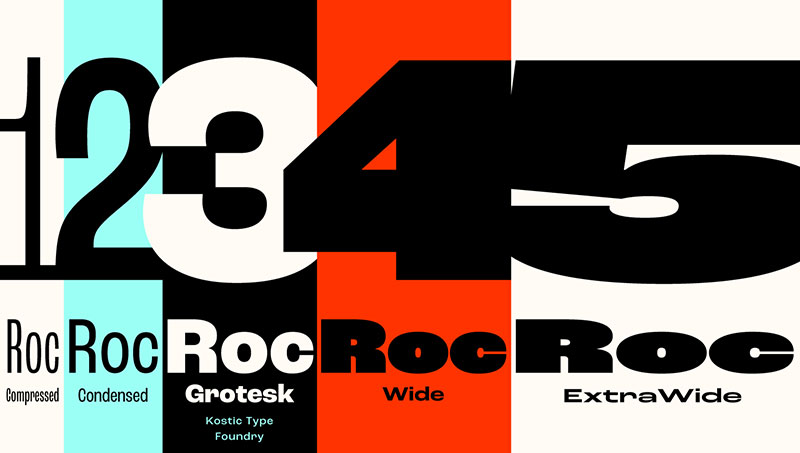
Stellen Sie sich vor, Sie tauchen in eine Welt ein, in der jeder Buchstabe eine Geschichte erzählt. Das ist die Kraft der besten Schriften für Grafikdesign.
Schriften sind mehr als nur Buchstaben auf einer Seite; sie sind die Stimme Ihrer Marke, der Ton Ihrer Nachricht und die Persönlichkeit Ihres Designs.
Auf dieser Reise werden wir das Geheimnis hinter der Auswahl der perfekten Schrift lüften. Egal, ob Sie ein schlankes Logo entwerfen oder eine herausragende Webseite gestalten, die richtige Schrift kann Ihr Design machen oder brechen.
Ich werde Sie durch das Labyrinth von Serifen und serifenlosen Schriften führen, Sie mit dem Charme von Schreibschriften bekannt machen und Ihnen zeigen, wie Sie die Wirkung von Display-Schriften nutzen können.
Sie werden nicht nur über Ästhetik lernen, sondern auch über die Feinheiten der Schriftlesbarkeit und typografischen Trends.
Von der Kühnheit der Helvetica bis zur Eleganz der Garamond hat jede Schrift ihre eigene Geschichte. Am Ende werden Sie in der Lage sein, Schriftauswahlen zu treffen, die nicht nur gut aussehen, sondern auch viel aussagen.
Die besten Schriften für Grafikdesign
| Schrift | Kategorie | Serif/Serifenlos | Verwendung | Bemerkenswerte Merkmale |
|---|---|---|---|---|
| Garamond | Altmodisch | Mit Serifen | Fließtext, Druck | Elegant, lesbar, Stil der französischen Renaissance |
| Baskerville | Übergangszeit | Mit Serifen | Druck, Luxus | Scharf, hoher Kontrast, Gefühl der englischen Aufklärung |
| Times New Roman | Übergangszeit | Mit Serifen | Zeitungen, Fließtext | Allgegenwärtig, kompakt, praktisch |
| Bodoni | Modern | Mit Serifen | Schlagzeilen, Poster | Extremer Kontrast zwischen dicken und dünnen Linien |
| Georgia | Modern | Mit Serifen | Digitale Bildschirme | Sehr lesbar auf Bildschirmen, robust |
| Financier Display | Neo-grotesk | Mit Serifen | Finanzberichte | Anspruchsvoll, zeitgenössisch, optimiert für Display-Nutzung |
| Helvetica | Neo-grotesk | Ohne Serifen | Allgemein, Beschilderung | Neutral, klar, sehr beliebt |
| Arial | Grotesk | Ohne Serifen | Allgemeine digitale Nutzung | Häufig, Alternative zu Helvetica |
| Univers | Grotesk | Ohne Serifen | Verschiedenes | Breites Spektrum an Varianten, klar, funktional |
| Futura | Geometrisch | Ohne Serifen | Branding, Poster | Geometrische Formen, modern |
| Avenir | Geometrisch | Ohne Serifen | Unternehmensdesign | Modern, humanistische Akzente, klar |
| Neue Haas Grotesk | Neo-grotesk | Ohne Serifen | Typografie, Branding | Ursprünglicher Name von Helvetica, originalgetreu |
| Blimey | Display | Ohne Serifen | Schlagzeilen, dekorativ | Ausdrucksstark, kreativ |
| Cheee | Display | Ohne Serifen | Leger, komödiantisch | Eigenartig, spaßig, informell |
| BD Supper | Display | Ohne Serifen | Poster, Branding | Fett, wirkungsvoll |
| Beverly Drive | Schreibschrift | Ohne Serifen | Branding, Mode | Elegante Kursivschrift |
| Swear Display | Mit Serifen | Redaktion, Luxus | Raffiniert, hoher Kontrast |
| Trade Gothic | Gotisch | Ohne Serifen | Werbung, Text | Direkt, unkompliziert |
| Roc Grotesk | Ohne Serifen | Allgemeine Nutzung | Vielseitig, zeitgenössisch, breites Gewichtsspektrum |
| Atyp | Display | Ohne Serifen | Poster, künstlerisch | Einzigartig, originell |
| Byker | Display | Ohne Serifen | Urban, jugendlich | Kantig, zeitgenössisch |
| Forrest | Handschrift | Ohne Serifen | Legerer Text, informell | Freundlich, organisch |
| MD Nichrome | Grotesk | Ohne Serifen | Web, Redaktion | Modern, minimalistisches Gefühl |
| Dunbar | Ohne Serifen | Display | Schlagzeilen, Luxus | Große x-Höhe, stilisiert |
| Gooper | Display | Ohne Serifen | Poster, auffällig | Klobig, übertrieben |
| Bilo | Display/Dekorativ | Ohne Serifen | Spaßthemen, verspielt | Handgezeichnet, informell |
Beliebte Serifenschriften
Serifenschriften, diese klassischen Schönheiten mit kleinen Füßen am Ende jedes Buchstabens, sind ein Eckpfeiler in der Welt der besten Schriften für Grafikdesign.
Sie bringen einen Hauch von Eleganz, Tradition und ein gewisses ‚je ne sais quoi‘ auf den Tisch. Tauchen wir ein und erkunden einige der bekanntesten und zeitlosesten Serifenschriften sowie einige moderne Interpretationen dieses klassischen Stils.
Zeitlose Klassiker
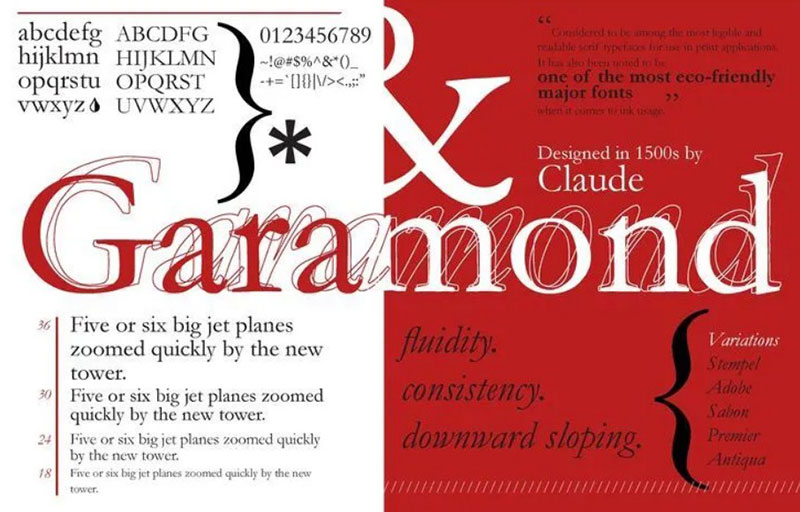
Garamond, ah, die alte Seele der Typografie. Es ist wie dieser Vintage-Wein – wird mit der Zeit immer besser.
Perfekt für diejenigen, die einen Hauch von Geschichte in ihren Designs lieben. Garamond ist nicht nur eine Schrift; es ist ein Geschichtenerzähler, der seit dem 16. Jahrhundert existiert und damit eine erste Wahl für Buchgestalter und Verleger ist.
Mit seiner klassischen Eleganz und Lesbarkeit nimmt Garamond einen besonderen Platz im Herzen der Typografie ein.
Weiter geht’s mit Baskerville. Diese Schrift balanciert die feine Linie zwischen Respektabilität und Flair.
Im 18. Jahrhundert entworfen, hat Baskerville diese einzigartige Fähigkeit, jeden Text sofort anspruchsvoller aussehen zu lassen. Es ist wie der maßgeschneiderte Anzug der Schriftwelt – sieht immer gut aus, egal zu welchem Anlass.
Und dann gibt es das allgegenwärtige Times New Roman. Lieben oder hassen Sie es, man kann seine Omnipräsenz nicht leugnen.
Es ist wie das Brot und Butter der Schriften – zuverlässig, vertraut und erledigt die Arbeit. Obwohl es manche als ‚Standard‘ bezeichnen mögen, ist Times New Roman in der Welt der besten Schriften für Grafikdesign ein Klassiker, der bleiben wird.
Moderne Serifenschriften
Jetzt wird es aufregend mit einigen modernen Serifenschriften. Bodonimit seinem dramatischen Kontrast zwischen dicken und dünnen Strichen schreit nach Luxus.
Es ist wie das High-Fashion-Model der Schriften – glamourös und auffällig. Perfekt für Schlagzeilen, Logos und jedes Projekt, bei dem Sie eine Aussage machen möchten.
Als Nächstes, Georgia. Speziell für die Lesbarkeit auf Bildschirmen entwickelt, ist es der freundliche Nachbar unter den Serifenschriften.
Anspruchslos, vielseitig und selbst in kleinen Größen gut lesbar, ist Georgia eine solide Wahl für Webinhalte und digitales Design.
Zu guter Letzt, Financier Display. Diese Schrift bringt einen zeitgenössischen Twist zum traditionellen Serifen.
Es ist wie jener coole, raffinierte Freund, der weiß, wie man die Dinge interessant hält. Mit seiner starken Persönlichkeit und hohen Lesbarkeit ist Financier Display großartig für moderne Marken, die sich abheben wollen.
Einflussreiche serifenlose Schriften
Serifenlose Schriften sind wie der coole, minimalistische Cousin in der Familie der besten Schriften für Grafikdesign.
Sie sind sauber, klar und oh-so-modern. Serifenlose Schriften verzichten auf die kleinen Füße (Serifen) für einen gestraffteren, geradlinigeren Look.
Perfekt für alles, von kräftigen Schlagzeilen bis hin zu leicht lesbarem Fließtext, sind diese Schriften eine erste Wahl für Grafikdesigner, die eine schlanke Aussage machen möchten.
Klassische serifenlose Schriften
Zuerst sprechen wir über Helvetica. Sie ist wie das Schweizer Taschenmesser der Schriften – vielseitig, funktional und super beliebt.
Helvetica ist überall, von U-Bahn-Schildern bis zu Logos von Technologieunternehmen. Sie ist der Inbegriff der Philosophie ‚weniger ist mehr‘ im Design.
Schlicht und doch kraftvoll ist Helvetica ein Muss in jedem Designer-Toolkit.
Dann gibt es Arial. Denken Sie daran als jüngeren Geschwister von Helvetica. Es ist super häufig (Sie haben es wahrscheinlich auf Ihrem Computer gesehen) und unglaublich benutzerfreundlich.
Arial ist wie der freundliche Nachbar, der immer da ist, wenn Sie ihn brauchen. Es ist großartig für digitale Projekte, besonders wenn Lesbarkeit wichtig ist.
Und wir dürfen nicht Univers vergessen. Diese Schrift dreht sich alles um Konsistenz und Klarheit. Es ist wie der methodische, organisierte Freund, der Sie nie im Stich lässt.
Mit einer Reihe von Gewichten und Stilen bietet Univers Flexibilität und behält dabei sein sauberes, ungehindertes Erscheinungsbild bei. Es ist eine Top-Wahl für Unternehmens- und Redaktionsdesign.
Zeitgenössische serifenlose Schriften
Jetzt zu den neueren Stars der serifenlosen Welt. Futura ist wie der fortschrittliche, trendsetzende Schrifttyp.
Mit seinen geometrischen Formen und gleichmäßiger Gewichtsverteilung hat es eine futuristische Atmosphäre, die perfekt für innovative Marken und moderne Kunstprojekte ist.
Als nächstes, Avenir. Diese Schrift ist wie der coole, jüngere Cousin von Futura. Es geht mehr um Balance und Harmonie, weniger um scharfe Kanten.
Avenir bringt eine Note Wärme in die oft kalte und unpersönliche Welt der serifenlosen Schriften. Es ist großartig für Benutzeroberflächen, digitale Inhalte und überall dort, wo Sie einen Hauch von moderner Eleganz wünschen.
Zuletzt, aber definitiv nicht zuletzt, Neue Haas Grotesk. Denken Sie daran als die ursprüngliche, ungefilterte Version von Helvetica.
Es hat etwas mehr Charakter, etwas mehr Eigenart. Neue Haas Grotesk ist für diejenigen, die Helvetica lieben, aber etwas mit etwas mehr Persönlichkeit möchten.
Einzigartige Display- und Schreibschriften
Wenn wir über die besten Schriften für Grafikdesign sprechen, ist es wie eine Schatzkiste zu öffnen, wenn wir über einzigartige Display- und Schreibschriften sprechen.
Diese sind nicht Ihre alltäglichen Schriftarten; sie sind die Showstopper, diejenigen, die Ihr Design schreien lassen ‚Schau mich an!‘.
Sie sind perfekt, wenn Sie Persönlichkeit, Flair und ein wenig Drama in Ihre Arbeiten einbringen müssen. Lassen Sie uns einige dieser bahnbrechenden Schriften durchgehen.
Display-Schriften für Impact
Schon mal von Blimey gehört? Es ist wie das Leben der Party in der Schriftwelt. Fett, laut und unverschämt spaßig, Blimey ist perfekt, um Aufmerksamkeit zu erregen. Verwenden Sie es für Schlagzeilen, Poster oder jedes Projekt, bei dem Sie möchten, dass die Worte vom Bildschirm oder von der Seite springen.
Cheee ist ein weiteres Juwel. Stellen Sie sich den schrulligen Freund vor, der immer in einer Menschenmenge auffällt. Cheee ist einzigartig, verspielt und perfekt für Projekte, die ein wenig Verspieltheit benötigen. Es ist großartig für kreative Branding, funky Anzeigen oder sogar, um ein wenig Funken in Social-Media-Grafiken zu bringen.
Dann gibt es BD Supper. Stellen Sie sich eine Schrift vor, die sowohl stark als auch elegant ist, wie ein gut geschnittener Anzug. Es ist anspruchsvoll, aber nicht steif, was es ideal für High-End-Branding, Magazin-Header oder jedes Design macht, das einen Hauch von Klasse benötigt.
Elegante Schreibschriften
Wenn wir zur eleganten Seite der Dinge wechseln, sind Schreibschriften wie Beverly Drive die handgeschriebenen Liebesbriefe der Schriftwelt.
Beverly Drive mit seinen sanften, fließenden Linien fügt jedem Projekt eine persönliche, handgemachte Note hinzu. Es ist perfekt für Hochzeitseinladungen, Boutique-Branding oder alles, was einen Hauch von Eleganz benötigt.
Swear Display ist eine weitere Schönheit. Denken Sie daran als den künstlerischen, freigeistigen Typ. Es ist perfekt, wenn Sie ein wenig Flair und Raffinesse hinzufügen möchten. Ideal für Buchcover, Branding oder jedes Projekt, bei dem Sie möchten, dass die Schrift nicht nur gesehen, sondern gefühlt wird.
Vielseitige und funktionale Schriften
Wenn wir über die besten Schriften für Grafikdesign sprechen, sind Vielseitigkeit und Funktionalität der Schlüssel.
Dies sind die Schriften, die alles können – von laut schreiend auf einem Poster bis hin zu sanft flüsternd in einem Bericht. Sie sind wie das Multitool in Ihrem Design-Kit. Lassen Sie uns einige Schriften durchgehen, die ziemlich alles bewältigen können, was Sie ihnen anvertrauen.
Arbeitsschriften für verschiedene Anwendungen
Trade Gothic ist wie dieser zuverlässige Freund, der immer für Sie da ist. Es ist unkompliziert, nüchtern und erledigt die Arbeit.
Diese Schrift ist perfekt für die Zeiten, in denen Sie möchten, dass Ihre Nachricht klar und ungehindert ist. Es ist großartig für alles, von Fließtext in einem Bericht bis hin zu einer starken Schlagzeile in einer Anzeige.
Als nächstes, Roc Grotesk. Denken Sie daran als das Chamäleon der Schriftwelt. Es passt nahtlos in jedes Design, an dem Sie arbeiten Entschuldigen Sie bitte die Unterbrechung. Lassen Sie uns den Abschnitt fortsetzen.
Roc Grotesk ist wie das Chamäleon der Schriftwelt. Es passt nahtlos in jedes Design, an dem Sie arbeiten. Mit seiner breiten Palette an Gewichten kann Roc Grotesk laut oder leise, oder alles dazwischen sein. Es ist super vielseitig, was es zu einer Top-Wahl für Branding, Webdesign und redaktionelle Arbeit macht.
Und dann gibt es Atyp. Diese Schrift ist wie der coole, kantige Typ in der Gruppe. Sie ist modern, dynamisch und sticht hervor. Verwenden Sie Atyp, wenn Sie Ihrem Design eine zeitgenössische Wendung geben möchten. Es ist großartig für kreative Projekte, digitalen Inhalt und überall dort, wo Sie eine Aussage machen möchten.
Schriften für Spezialanwendungen
Manchmal benötigen Sie eine Schrift, die für einen bestimmten Zweck gemacht ist. Byker ist wie der Technikwizard in der Schriftwelt. Entworfen für technische Projekte, hat es ein mechanisches Gefühl, das perfekt für alles von Bedienungsanleitungen bis zu technischen Zeichnungen ist.
Forrest ist eine weitere spezielle Schrift. Stellen Sie sich eine warme, ansprechbare Schriftart mit einer Prise Eigenartigkeit vor. Forrest ist eine abgerundete Serifenschrift, die sich von der Masse abhebt. Sie ist perfekt für Kinderbücher, spielerisches Branding oder jedes Projekt, das eine freundliche Note benötigt.
Aktuelle Trends in der Typografie
In der sich ständig weiterentwickelnden Welt der besten Schriften für Grafikdesign ist es aufregend, die neuesten Trends zu verfolgen – es ist spannend und absolut lohnenswert.
Typografietrends sind der Herzschlag der Designinnovation und formen ständig neu, wie wir visuell ausdrücken und kommunizieren. Tauchen wir ein, was gerade Wellen schlägt.
Retro- und nostalgische Einflüsse
Zuerst sprechen wir über die Comeback-Kinder – Retro- und nostalgische Einflüsse. Schriften wie MD Nichrome bringen die Vibes vergangener Jahre mit einem modernen Dreh zurück.
Es ist, als hätte man einen Fuß in der Vergangenheit, während die Augen auf die Zukunft gerichtet sind. Diese Schriften vermischen alten Charme mit zeitgenössischem Flair und sind perfekt für Marken, die mit einem Hauch von Nostalgie auffallen möchten.
Dann gibt es Dunbar. Es ist wie das typografische Äquivalent einer klassischen Vinylplatte – zeitlos und voller Charakter.
Mit seinen Wurzeln in der Vergangenheit und einem schlanken, modernen Finish überbrückt Dunbar die Kluft zwischen Retro- und zeitgenössischem Design und bietet jedem Projekt einen einzigartigen Geschmack.
Innovative und eigenwillige Designs
Jetzt wird’s eigenwillig. Schriften wie Gooper sind alles darum, die Form zu sprengen. Sie sind die Regelbrecher, die Ausreißer, diejenigen, die Sie zweimal hinsehen lassen.
Gooper und seine Verwandten sind perfekt für Projekte, die unkonventionell, verspielt oder einfach nur völlig anders sein sollen.
Und übersehen Sie nicht Bilo. Diese Schrift ist wie dieser eine Freund, der immer außerhalb der Box denkt.
Bilo ist eigenwillig, spaßig und unverschämt einzigartig, was es zu einer großartigen Wahl für kreative Projekte macht, die Grenzen überschreiten und Aufmerksamkeit erregen wollen.
Schriftkombination und Nutzungstipps
Schriften zu kombinieren ist wie das Mischen des perfekten Cocktails – es ist eine Kunst. In der Welt der besten Schriften für Grafikdesign zu wissen, wie man Schriften kombiniert, kann Ihr Design von gut zu unvergesslich steigern. Hier sind einige Tipps, um Ihnen den Einstieg zu erleichtern.
Strategien für effektive Schriftkombinationen
Kontrast ist entscheidend. Mischen und kombinieren Sie verschiedene Schriftstile – wie eine fette Serifenschrift mit einer leichten serifenlosen –, um visuelles Interesse und Hierarchie zu schaffen. Es ist wie ein Gespräch zwischen verschiedenen Elementen Ihres Designs.
Halten Sie es ausgeglichen. Das Kombinieren einer sehr dekorativen Schrift mit einer zurückhaltenderen kann eine harmonische Balance schaffen. Es ist wie das Yin und Yang der Typografie, wobei jedes das andere ergänzt.
Berücksichtigen Sie die Stimmung. Die von Ihnen ausgewählten Schriften sollten zum Ton und zur Stimmung Ihres Projekts passen. Es ist wie die Wahl des richtigen Outfits für den Anlass – es sollte genau passen.
Überlegungen zur Lesbarkeit und Ästhetik
Lesbarkeit ist äußerst wichtig. Stellen Sie immer sicher, dass Ihr Text leicht zu lesen ist, insbesondere bei längeren Inhalten. Es ist, als würde man sicherstellen, dass der Weg klar und einfach zu gehen ist.
Ästhetik ist wichtig. Die Schriften sollten nicht nur funktional sein, sondern auch zur Gesamtschönheit Ihres Designs beitragen. Es geht darum, sicherzustellen, dass alles genauso gut aussieht, wie es funktioniert.
Seien Sie konsistent. Verwenden Sie dieselben Schriften in Ihrem Projekt für ein kohärentes Erscheinungsbild. Es ist, als hätte man ein durchgängiges Thema, das durch jeden Teil Ihres Designs läuft.
FAQ zu den besten Schriften für Grafikdesign
Was macht eine Schrift gut für Grafikdesign?
Der Schlüssel liegt in Vielseitigkeit und Klarheit. Eine gute Schrift sollte sich gut über verschiedene Medien hinweg eignen, egal ob es sich um Druck oder Digital handelt.
Sie sollte auch lesbar sein und das Gesamtdesign ergänzen. Denken Sie darüber nach, wie sie zur Stimmung des Projekts und zur Botschaft, die Sie vermitteln möchten, passt.
Wie wähle ich die richtige Schrift für mein Design?
Beginnen Sie, indem Sie den Kontext des Projekts berücksichtigen. Ist es formell oder lässig? Modern oder traditionell? Denken Sie dann über Lesbarkeit und Lesefreundlichkeit nach, besonders bei längeren Texten.
Stellen Sie abschließend sicher, dass die Schrift die Persönlichkeit der Marke oder die Botschaft Ihres Designs widerspiegelt. Es ist eine Mischung aus Funktionalität und Ästhetik.
Sind Serifen- oder serifenlose Schriften besser für Webdesign?
Das hängt vom Projekt ab. Serifenlose Schriften, bekannt für ihr sauberes und modernes Aussehen, sind im Allgemeinen auf Bildschirmen besser lesbar.
Serifenschriften können jedoch einen Hauch von Eleganz verleihen und eignen sich großartig für traditionellere oder literarische Inhalte. Berücksichtigen Sie immer die Lesbarkeit und den gesamten Designstil.
Kann ich mehrere Schriften in einem einzigen Design verwenden?
Absolut, aber tun Sie es weise. Beschränken Sie sich auf zwei oder drei Schriften, um Unordnung zu vermeiden.
Stellen Sie sicher, dass sie einander ergänzen – wie eine fette Display-Schrift für Überschriften und eine einfachere Schrift für Fließtext. Dies schafft eine visuelle Hierarchie und hält Ihr Design kohärent.
Welche sind einige häufige Fehler bei der Schriftauswahl?
Die Wahl übermäßig dekorativer Schriften, die die Lesbarkeit opfern, ist ein großes No-Go. Auch die Verwendung zu vieler verschiedener Schriften kann Ihr Design chaotisch wirken lassen.
Ein weiterer Fehler ist, die Stimmung und den Ton des Inhalts nicht zu berücksichtigen – die Schrift sollte zur Nachricht passen.
Wie wichtig ist die Schriftlesbarkeit im Grafikdesign?
Sehr wichtig. Wenn Ihr Publikum Mühe hat, Ihren Inhalt zu lesen, scheitert das Design an seiner Hauptfunktion. Besonders im digitalen Design, wo Nutzer oft Inhalte überfliegen, geht es bei der Lesbarkeit nicht nur um Ästhetik; es geht um effektive Kommunikation.
Was ist der Trend bei Schriften für Grafikdesign im Jahr 2023?
Wir sehen einen Anstieg bei eigenwilligen, einzigartigen Schriften, die traditionelle Regeln brechen – denken Sie an unkonventionelle Formen und fette Linien.
Es gibt auch eine wachsende Vorliebe für retro und nostalgische Schriften, die alten Charme mit modernen Drehungen vermischen. Es geht darum, herauszustehen und eine Aussage zu machen.
Wie paare ich Schriften effektiv?
Denken Sie an Kontrast und Harmonie. Kombinieren Sie eine fette Schrift mit einer neutraleren für Ausgewogenheit. Stellen Sie sicher, dass sie ein gemeinsames Designelement teilen, wie Buchstabenhöhe oder Strichstärke, für Harmonie.
Es ist, als würde man ein Gespräch zwischen verschiedenen Elementen in Ihrem Design schaffen.
Welche sind einige Go-To-Schriften für professionelle Designs?
Helvetica und Arial sind Klassiker für ein sauberes, professionelles Aussehen. Für etwas Eleganteres sind Garamond und Times New Roman großartige Optionen. Diese Schriften sind wie die vertrauenswürdigen Basics in Ihrem Kleiderschrank – vielseitig und immer angemessen.
Wie kann ich mein Design mit Schriften hervorheben?
Experimentieren Sie mit Schriftgewichten und -stilen. Verwenden Sie eine fette oder kursive Variante zur Betonung.
Spielen Sie mit Schriftgrößen und -farben, um Hierarchie und Fokus zu schaffen. Denken Sie daran, die richtige Schrift kann Ihr Design von gut zu unvergesslich verwandeln.
Fazit
Zum Abschluss unserer Tauchgänge in die Welt der besten Schriften für Grafikdesign ist klar, dass die richtige Schrift mehr als nur ein hübsches Gesicht ist. Sie ist die Stimme Ihres Designs, der stille Kommunikator, der Bände spricht. Von der zeitlosen Eleganz der Serifenschriften wie Garamond und Baskerville bis zur klaren Klarheit der serifenlosen Schriften wie Helvetica und Arial trägt jede Schrift ihre eigene Persönlichkeit und ihren eigenen Zweck.
- Merken Sie sich die Schlüsselpunkte:
- Stimmen Sie die Schrift mit der Stimmung Ihres Inhalts ab.
- Halten Sie die Lesbarkeit im Vordergrund, insbesondere bei längeren Texten.
- Scheuen Sie sich nicht davor, Schriften zu mischen, aber tun Sie dies mit einem scharfen Auge für Harmonie.
Ihre Wahl der Schrift kann Ihr Design machen oder brechen. Es ist wie die Wahl des richtigen Outfits für eine Gelegenheit – es sollte den Kontext passen, das Gesamterscheinungsbild verbessern und vor allem den einzigartigen Charakter Ihrer Marke oder Nachricht ausdrücken. Also gehen Sie voran und experimentieren, erkunden und finden Sie die perfekten besten Schriften für Grafikdesign, die Ihren Projekten ihre eigene unverwechselbare Stimme geben.